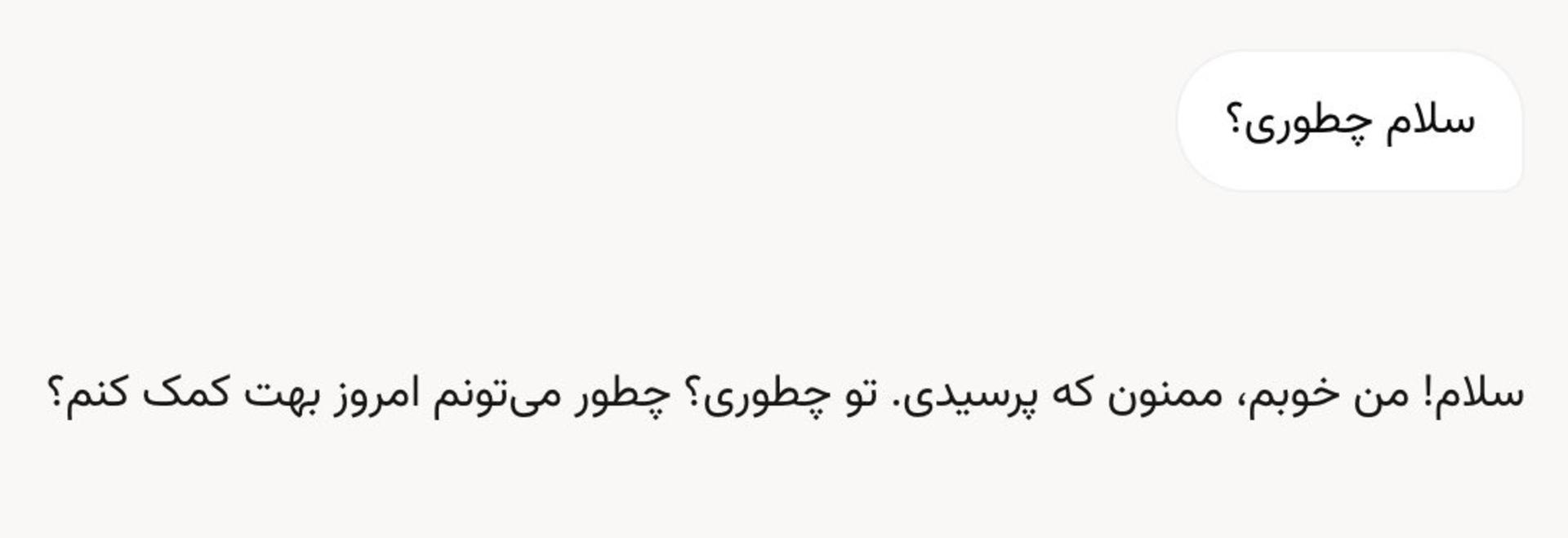
یکی از توسعهدهندگان ایرانی در استارتاپ xAI متعلق به ایلان ماسک، با انتشار پستی در ایکس خبر داد که فونت ایرانی وزیر به هوش مصنوعی گراک اضافه شده است.
فونتی که صابر راستی کردار خلق کرد، به چشم بسیاری از ایرانیها آشنا میآید؛ یکی از چشمنوازترین فونتهای فارسی که برای استفاده در صفحات وب و رابطهای کاربری تولید شده و بسیاری از المانهایش را از فونت DejaVu گرفته است.
صابر راستیکردار، برنامهنویس، طراح فونت و از اعضای فعال جامعهی نرمافزار آزاد و متنباز بود که در ۲۳ آبان ۱۴۰۲ در سن ۳۶ سالگی بر اثر ابتلا به سرطان ریه و لگن، چشم از جهان فرو بست.